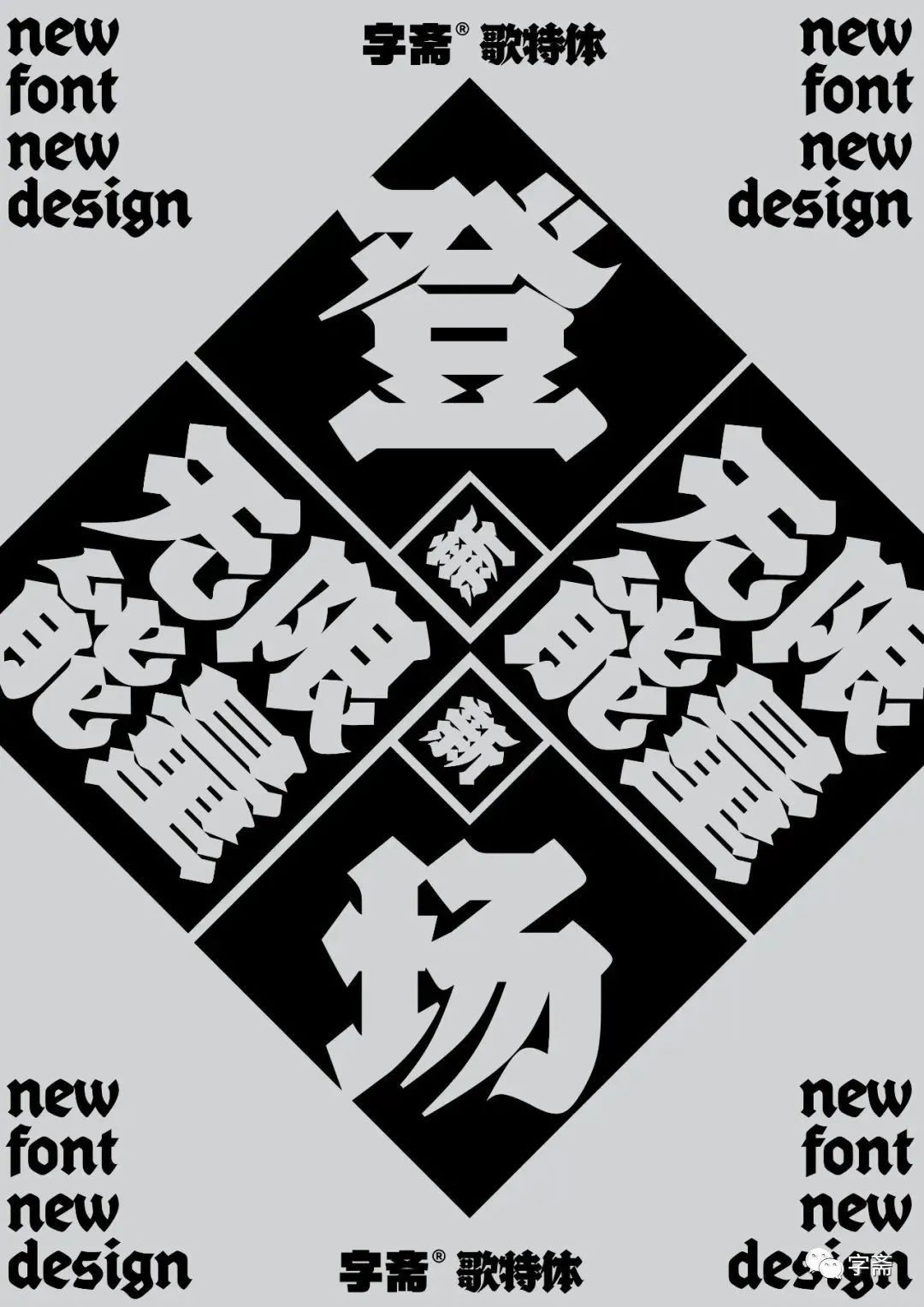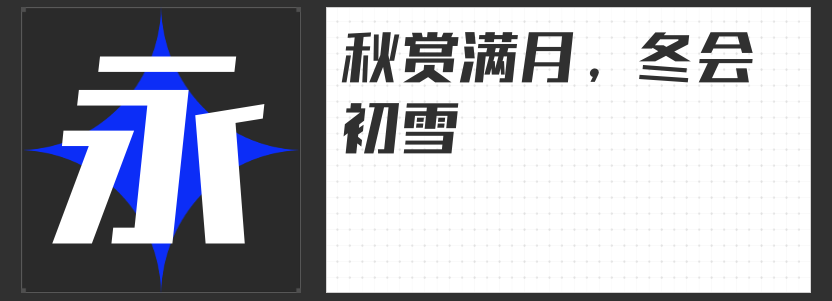
设计必备!四款字体推荐,让你的作品更具创意
在设计的世界中,字体的选择至关重要。它不仅能传达信息,更能表达情感、塑造风格。今天,我为大家推荐四款适合用于设计中的字库字体,它们各具特色,能为你的作品增添无限创意。
一、万人字造踏歌行体
这款字体以其独特的风格吸引了众多设计师的目光。结体方整严谨,笔画布局匀称又不失动感,使得整体风格既稳重又富有活力。用笔方整中带有圆润,略具斑驳感,笔力劲健,仿佛蓄势待发。单字笔画中透露出的古法用笔感觉,更是增强了整体风格特征,让作品在视觉上更具吸引力。无论是用于标题还是正文,都能展现出独特的韵味。
哥特风格以其高耸、尖锐的特点而著称,这款高手字斋哥特体Pro同样不例外。其独特的笔画设计和尖锐的线条,使得整体风格更加突出、醒目。无论是用于广告招牌、海报设计还是包装设计,都能迅速吸引人们的目光,传达出强烈的视觉冲击力。
三、高手兵克侠客体
这款字体以其粗犷、豪迈的风格而备受青睐。笔画设计粗犷有力,线条流畅自然,整体风格充满了力量感和动感。它适合用于需要展现力量、速度、冒险等元素的设计作品中,如游戏界面、运动品牌宣传等。
这款直线黑体以其硬朗倾斜的特点而脱颖而出。整体硬朗倾斜,中宫略大,布白均匀,重心统一。笔画设计简约而不失精致,横细竖粗,起笔收笔以平切为主,折笔处尖锐部分经过优化处理,更加和谐统一。整体倾斜约6度,视觉统一,使得整体风格更加协调、美观。无论是用于中文还是西文设计,都能展现出出色的搭配效果。
以上四款字体各具特色,适合用于不同类型的设计作品中。选择适合的字体,能让你的作品更加出色、更具创意。希望这些推荐能为你的设计之路提供一些灵感和帮助!